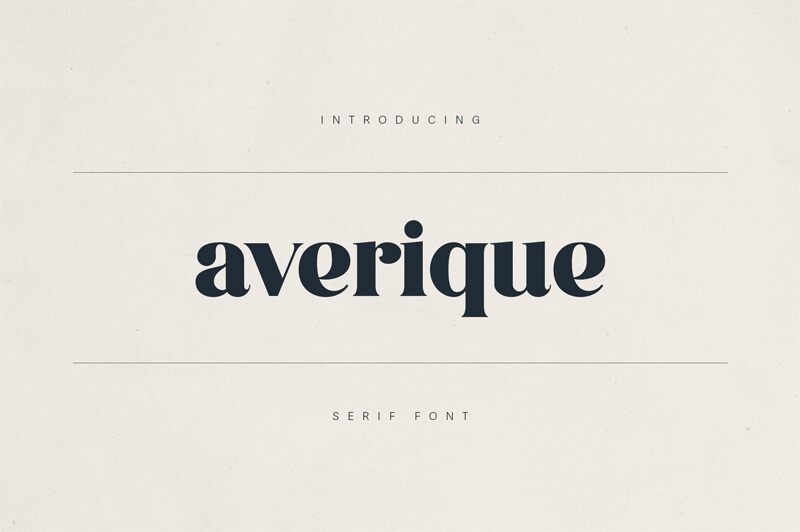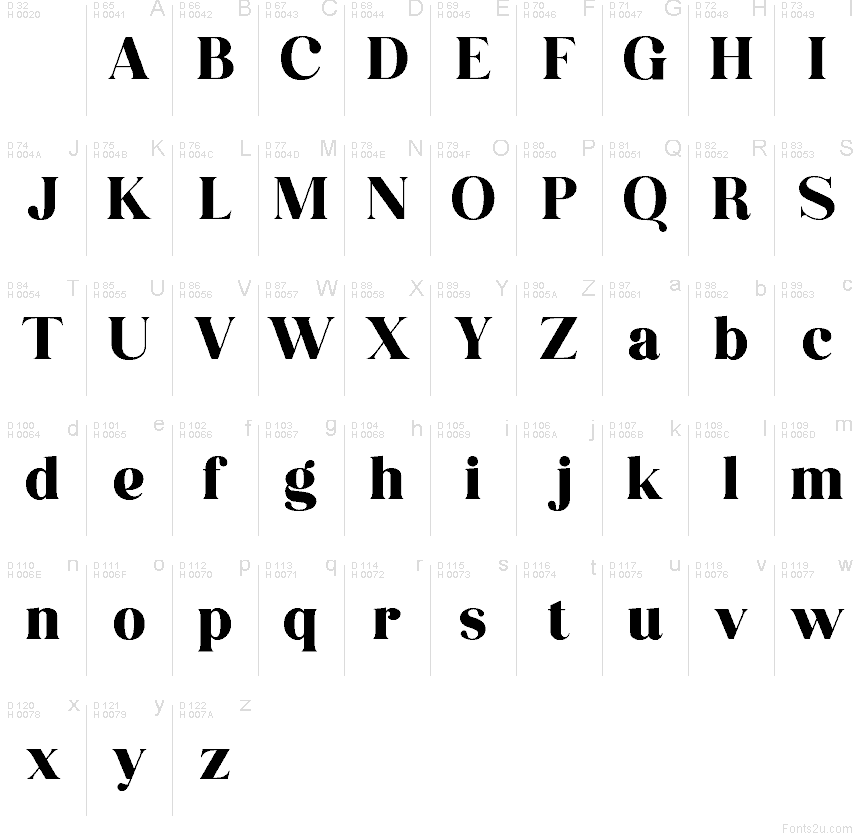
Averique Demo Regular
Averique ist eine kostenlose, kontrastreiche Serifenschrift mit einem modischen Editorial-Flair. Ihre Buchstaben kombinieren scharfe, präzise Serifen mit geschwungenen Kurven und eng geformten Verbindungen. Das verleiht der Schrift einen eleganten Rhythmus, der kultiviert wirkt, ohne dabei zu formell zu sein.
Diese kostenlose Schrift ist wie geschaffen für Magazin-Titel, Boutique-Branding, Parfümverpackungen, Buchcover und Titelkarten, bei denen ein Hauch von Drama gefragt ist. Sie eignet sich zudem hervorragend für kurze Überschriften und Monogramme, da die Kontraste und kompakten Kurven schon bei wenigen Zeichen ein durchdachtes, stilvolles Gesamtbild erzeugen.